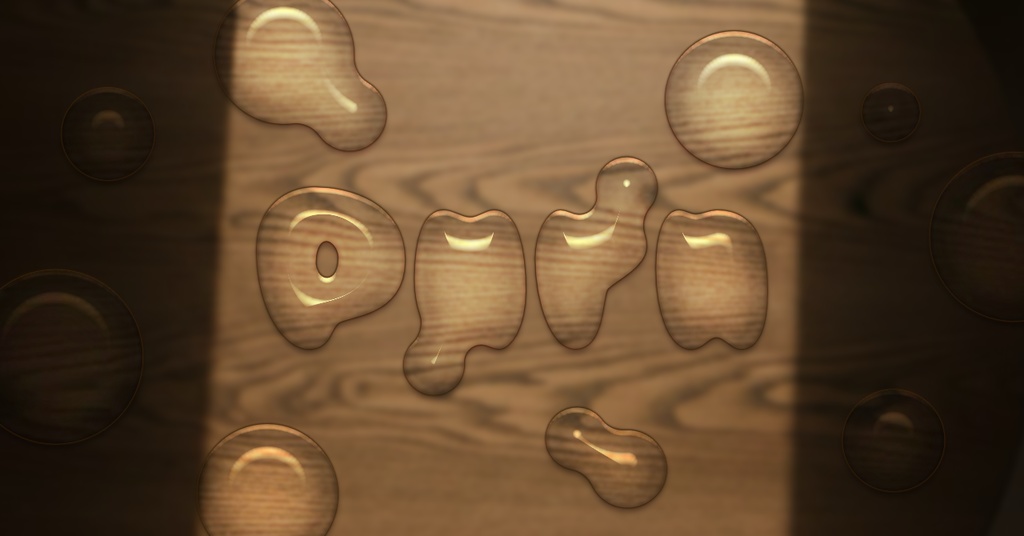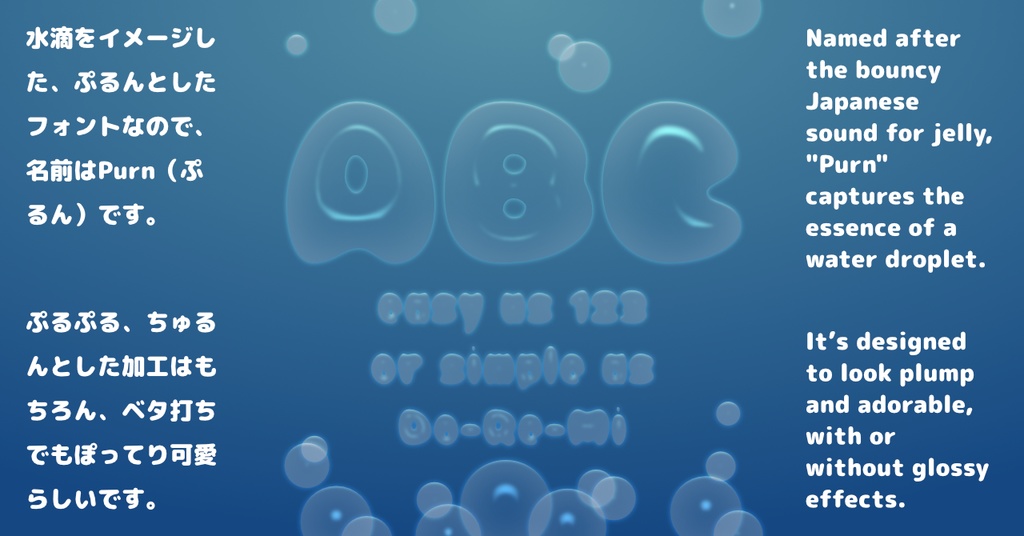
オリジナルフォント/Purn
☂︎Droplet Fontとは違うイメージで、水滴を表現したフォントです。 ☂︎「ぷるん」と読みます。 ☂︎大文字、小文字、英文記号を収録。 ☂︎.otf形式のフォントファイルです。 ☂︎こちらの商品は、ダウンロード販売となっております。決済完了後、購入履歴からダウンロードが可能です。